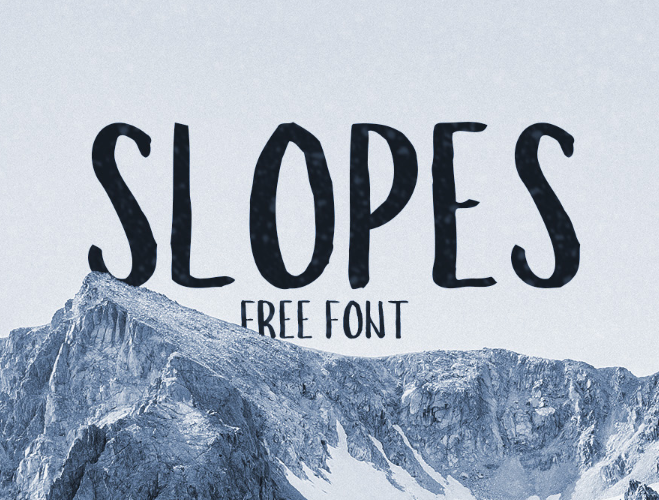
Introduzimos uma nova opção para designers e criadores de conteúdo na categoria das fóntes script: Slopes Brush Font. Desenvolvida pelo designer Hamilton, esta fonte é perfeita para quem busca um estilo à mão livre que remete ao handwriting tradicional. Ideal para aplicação em diversas tarefas, desde desenhos gráficos até criação de materiais vintage e artesanais. Slopes Brush Font está disponível com 400 caracteres em letras maiúsculas e minúsculas, números e símbolos especiais. Suporta uma gama completa de idiomas como Russo, Círlico, Europeu Central, Turco e mais, garantindo sua versatilidade para diversos mercados linguísticos. Com seu design cuidadosamente executado na estética da arte à mão livre, Slopes Brush Font é perfeito para aqueles que buscam uma fonte única e autêntica, sem perder a elegância e a sofisticação necessárias. Este produto do designer Boris Garic representa um passo em frente para quem busca incorporar personalidade e expressividade em seus projetos visuais.